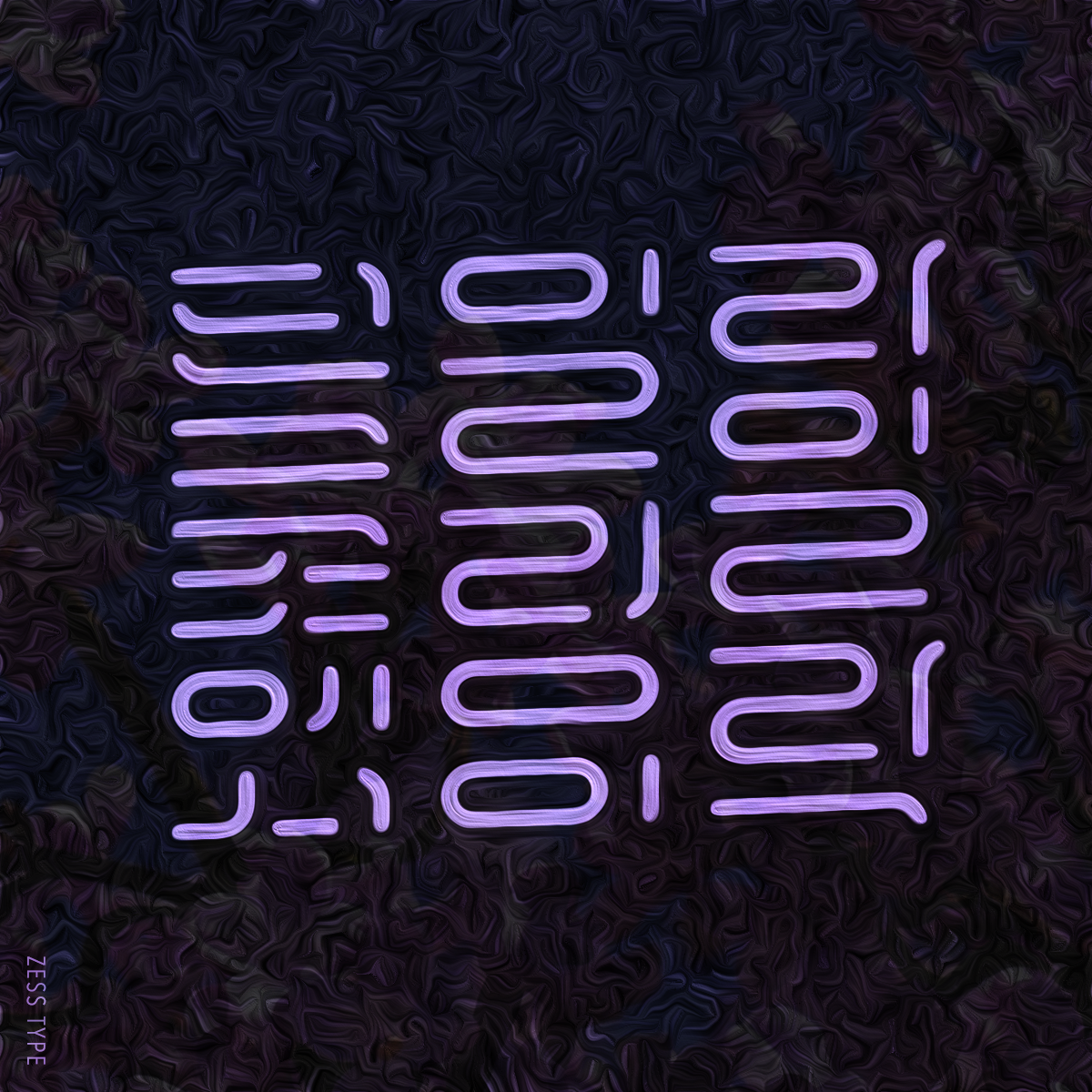
라일락 일렁이던 그곳에서
ZESSTYPE LETTERING WORK 2017
티테이블 프로젝트 <개화> 중.
아무튼. 나는 글자를 그린다. 애초에 읽히는 글자를 그리는 것이 아니라 그림으로서 보는 글자를 그리는 편이다.
지금이야 폰트 디자인을 하면서 읽는 글자를 훨씬 많이 그리고 있지만.
그래피티를 하던 그 때부터 지금까지 나는 글자를 텍스트보다는 이미지로서 생각하고 작업해왔다.
단순히 글자를 보기 좋게 그리기 보다는 내가 생각하고 느끼고 전달하고자 하는 것을 담아 의도적으로 글자를 그리고 표현한다.
대단한 의미나 메시지를 담아내는 작업들은 아니지만.
사람들이 이 글자들을 읽어주기 보다는 그저 봐주기를 원한다.
굳이 읽을 필요는 없다.
대단한 명문도. 멋진 메시지를 담고 있지도 않으니.
소소한 감상이다.
디자인보다는 아트웍에 가까운.
그런 작업들을 하고 있다.